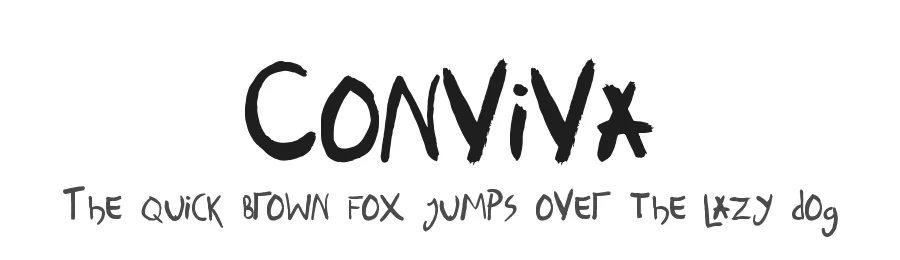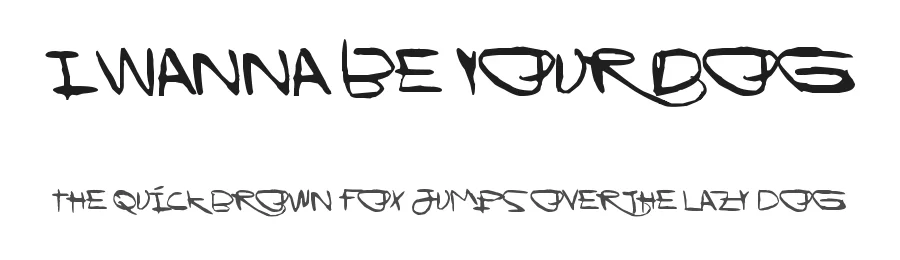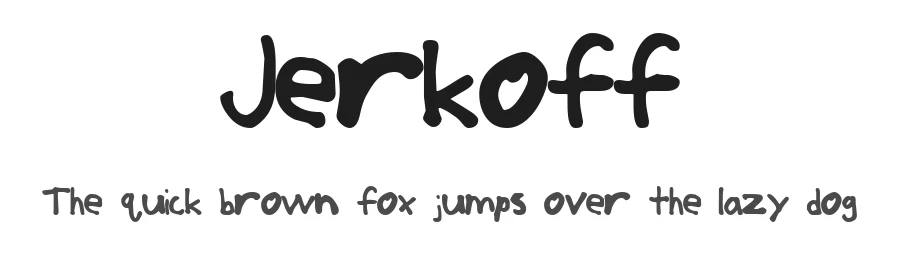
About Jose Fernandez Font
Font creada a partir de mi propia caligrafia.
Font created from my own letter.
Jose Fernandez Font is a script font that shines as a display or heading face. Pair it with a clean sans-serif or serif font for body text β the contrast creates a clear hierarchy while the two styles stay balanced and easy to read.